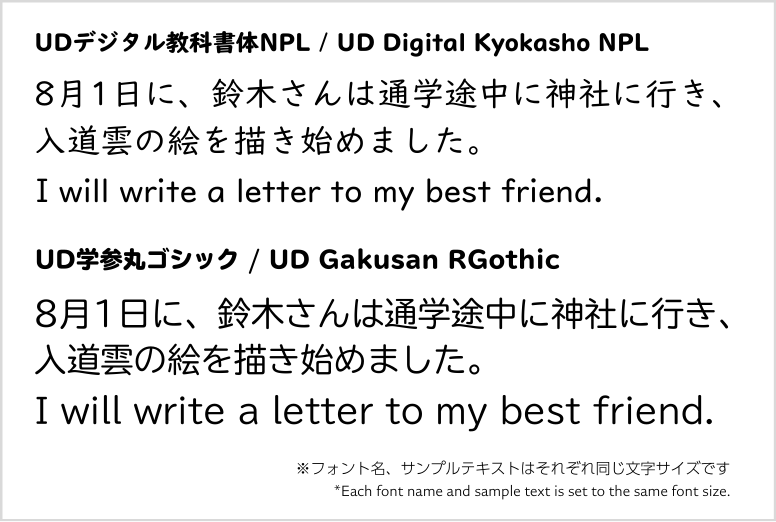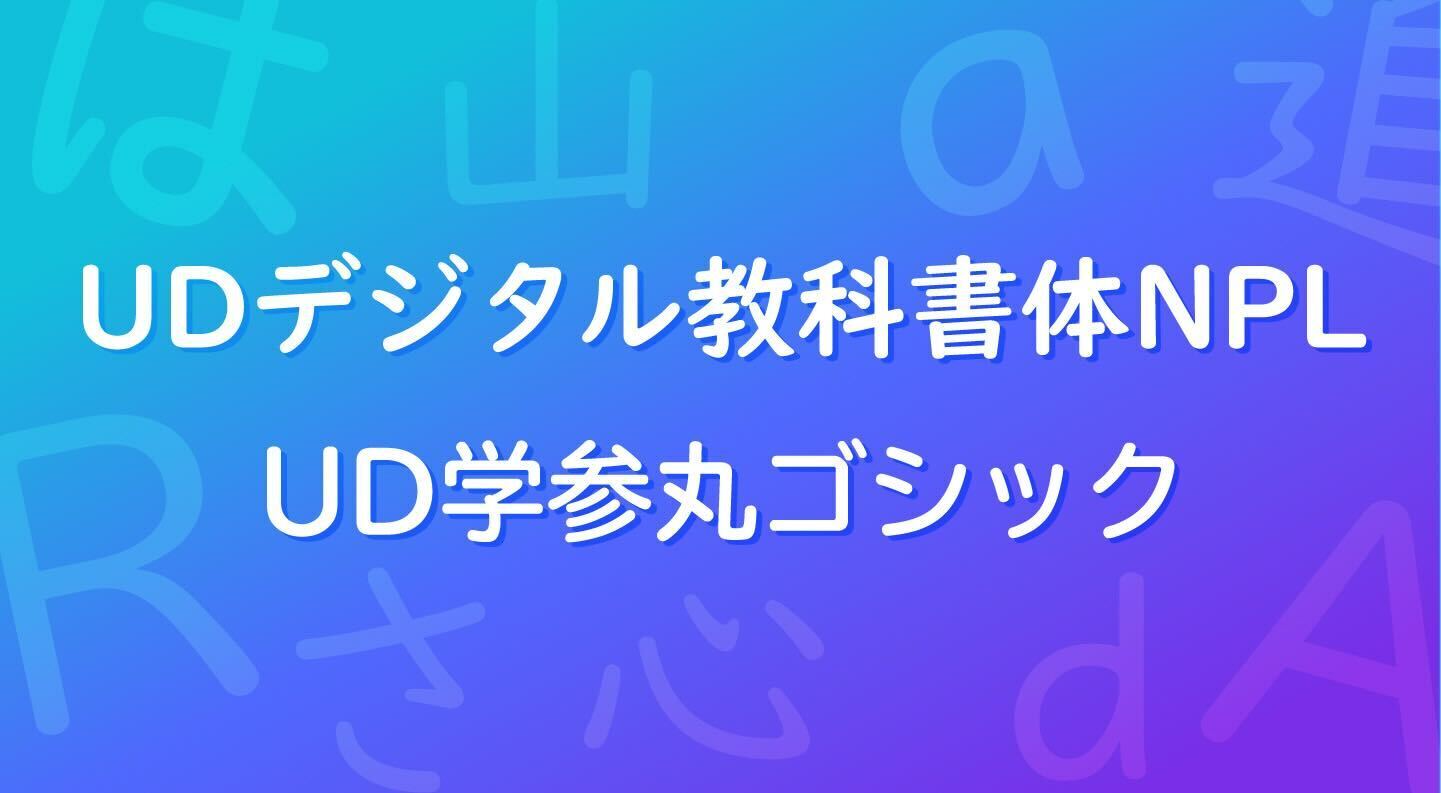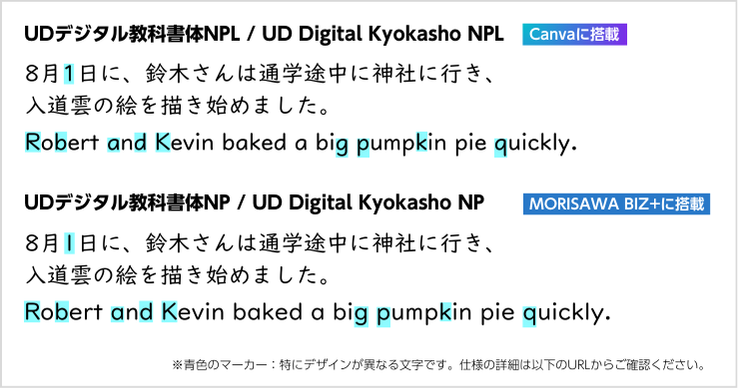
モリサワ ビジュアル・コミュニケーション・プラットフォーム「Canva」へ、「UDデジタル教科書体NPL」と「UD学参丸ゴシック」を提供開始、9月7日に記念イベントを開催
モリサワは、2023年12月よりCanvaにフォントを提供しています。近年、日本の教育現場においてもICT化が進む中、創造性を育むテクノロジーとツールの存在がかつてないほど重要となりました。こうした背景から、Canvaは多様なフォントやプレミアム機能が利用できるCanva 教育版を教員や生徒向けに無料提供し、多くの教育現場で活用されています。そのような環境に合わせ、今回、モリサワはより多くの方の教育や学習に役立てていただけるよう、教えやすく、学びやすい新しいUD(ユニバーサルデザイン)フォントを拡充します。
「UDデジタル教科書体NPL」と「UD学参丸ゴシック」は、教育におけるインクルーシブの実現に向けた、学びの環境の助けになる書体ラインナップとして、ロービジョン(弱視)やディスレクシア(読み書き障害)にも配慮できるクリエイティブ制作を実現します。フォントの選択肢が増えることで、学びの現場に携わる方々により多くの見え方・見えにくさ、読み書きの困難さに対応することができる環境をご提供します。
提供書体について
UDデジタル教科書体NPL
「UDデジタル教科書体NPL」は、ロービジョン(弱視)やディスレクシア(読み書き障害)に配慮したデザインの和文フォント「UDデジタル教科書体」と、同じコンセプトを持ちながら文部科学省の小学英語教材の欧文形状に準じた欧文フォント「UD Digikyo Latin」を1つのフォントに統合したCanva用オリジナルフォント(※)です。
■MORISAWA BIZ+で提供しているUDデジタル教科書体との違い
※「UDデジタル教科書体NPL」は「UDデジタル教科書体」と仕様が異なります。この2つのフォントに互換性はありません。
UD学参丸ゴシック
「UD学参丸ゴシック」は、教科書・教材のために開発された丸ゴシック体です。全ての和文の文字が文部科学省の学習指導要領の字形に準拠(学参化)しているため、「UDデジタル教科書体」と並んで、読み書きに困難さのある児童・生徒を含む多くの子どもたちの学習にお役立ていただけるフォントです。子どもたちの発達段階や使用目的などに合わせて、「UDデジタル教科書体」など他のUDフォントと併用したり、使い分けたりすることが可能です。
■UDデジタル教科書体NPLとUD学参丸ゴシックの違い
提供書体
UDデジタル教科書体NPL R/M/B/H
UD学参丸ゴシック R/B/H